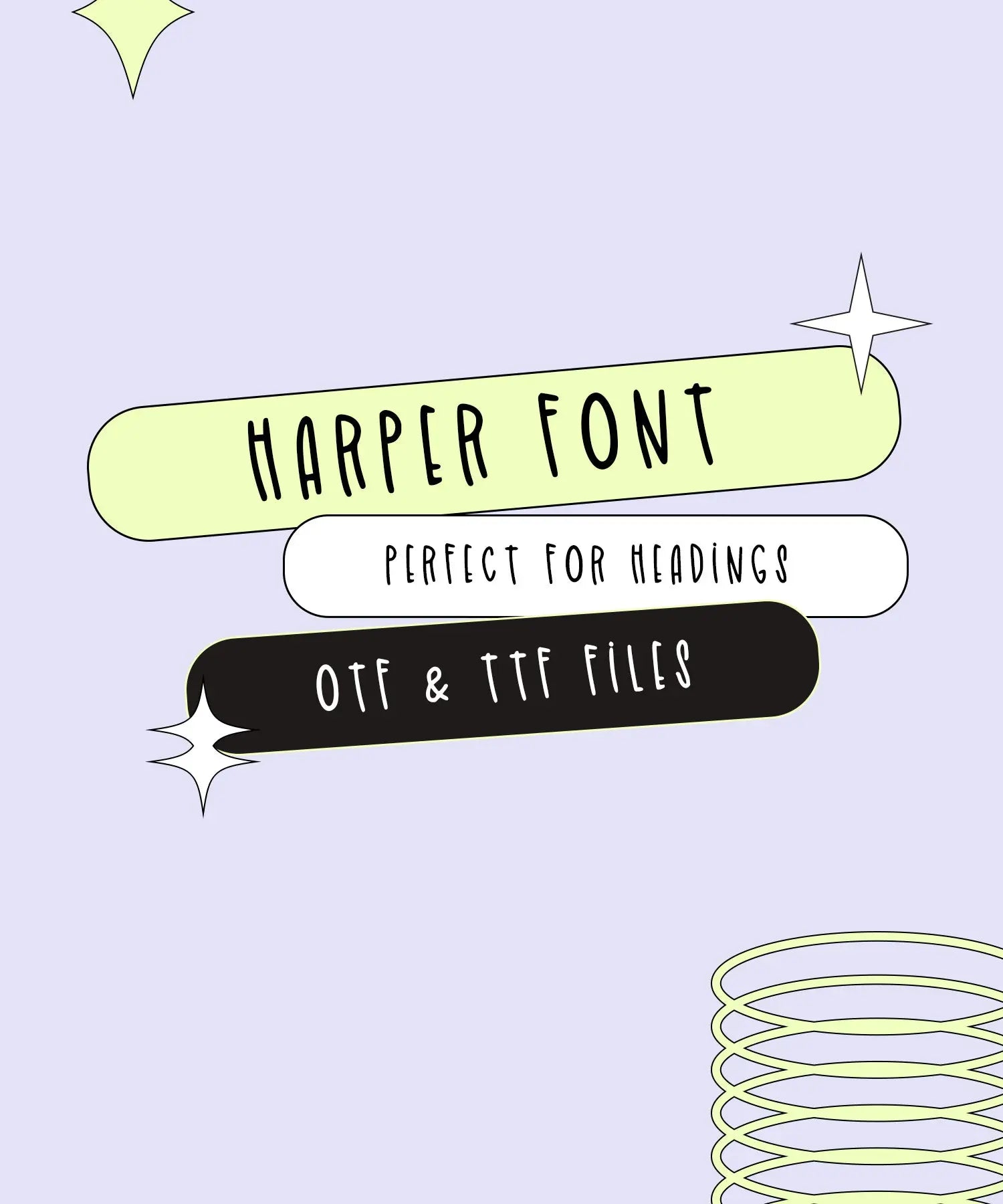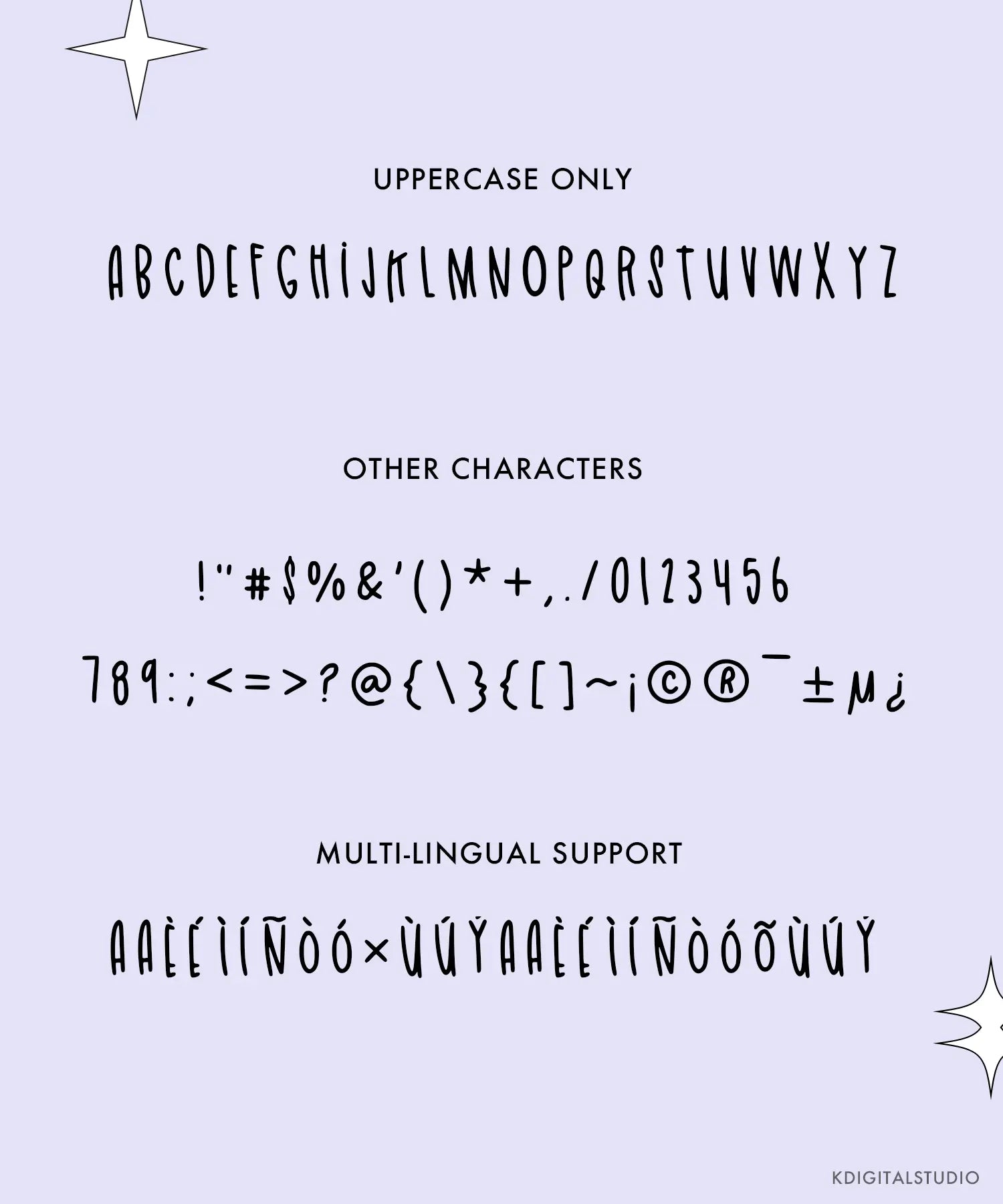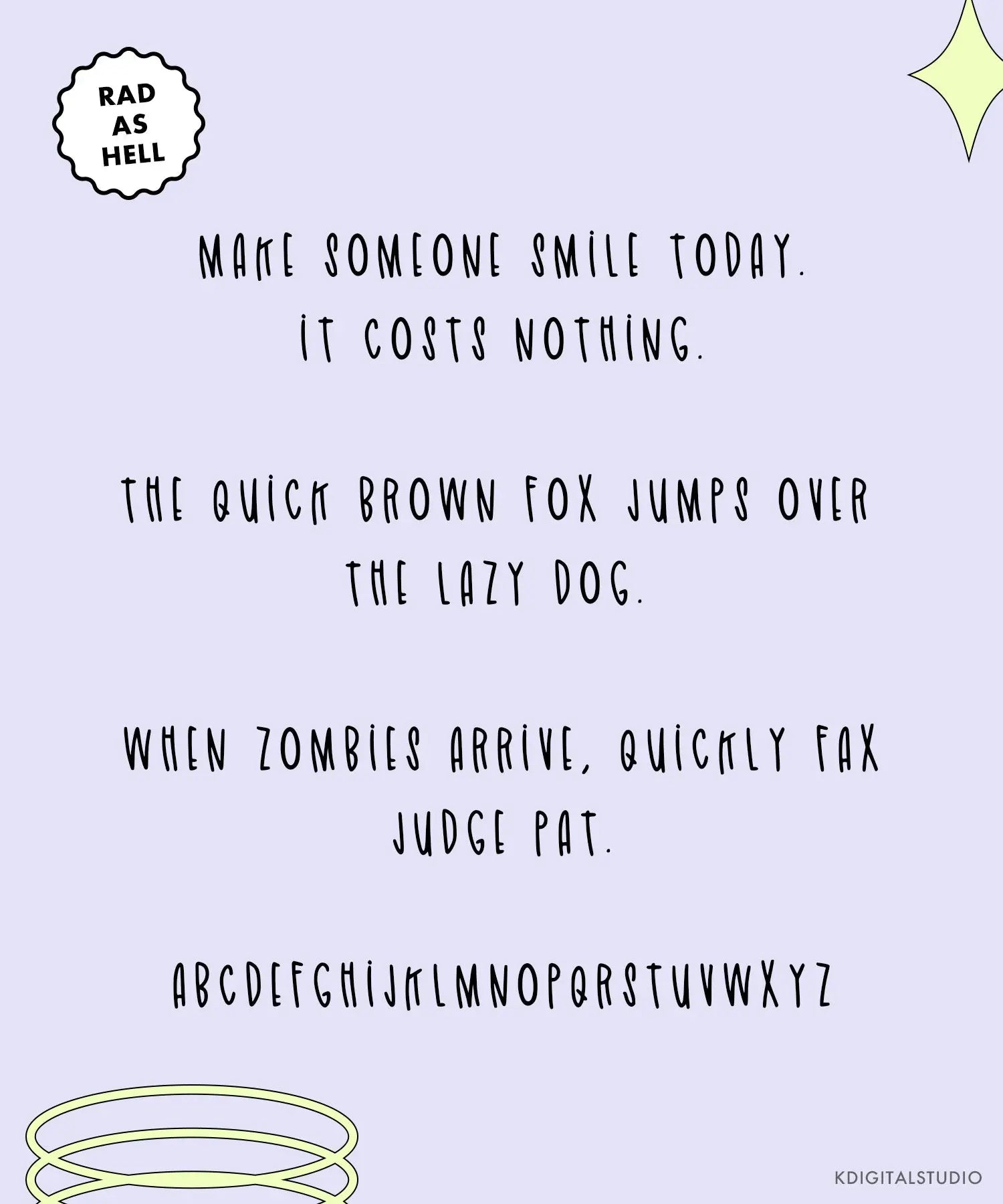
Fuente Harper
Esta fuente (solo) en mayúsculas está adorablemente escrita a mano y es perfecta para tomar notas o títulos. Ideal para agregar a tus proyectos Cricut o usar dentro de tus agendas digitales interactivas.